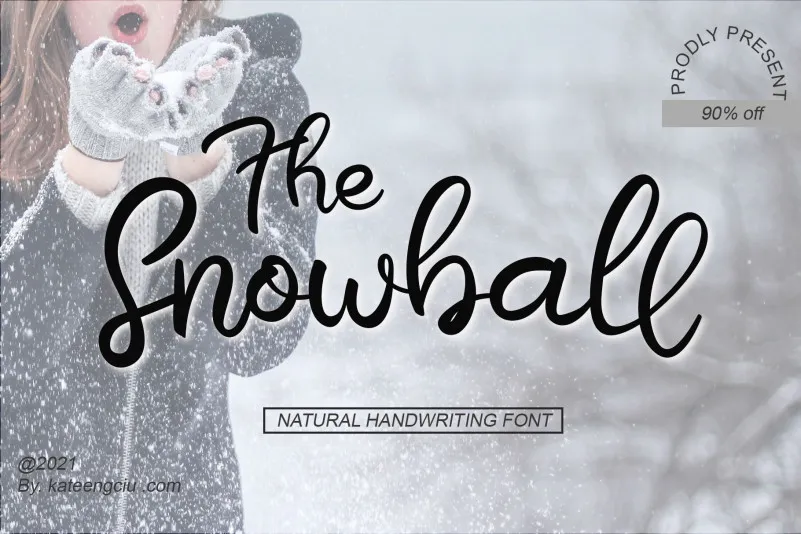
A Snowball Script Font é uma escolha perfeita para quem busca uma mistura sofisticada e atual. Inspirada nas influências chamigráficas clássicas, mantém um tom refinado que se torna acolhedor e fresco aos olhos. Seu desempenho versátil encanta desde os design de selos até os títulos, oferecendo uma linguagem única para cartões de presente ou quaisquer outros materiais de escritório. Com a Snowball Script Font, sua ideia pode ganhar vida com um toque elegante e moderno. Escolha esta fonte para dar um novo impulso à sua arte gráfica, seja você designer ou simplesmente alguém que aprecia uma maneira única de expressar seu trabalho.